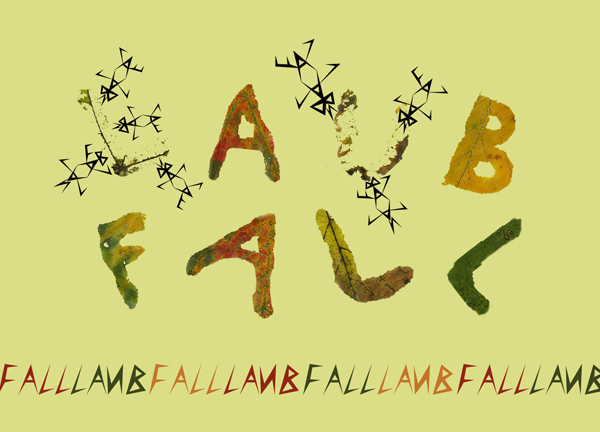
Cunei font gesucht
Hallo, auf meinem alten Computer (der sich für immer verabschiedet hat) war anscheinend eine Schrift vorinstalliert, die jetzt nicht mehr vorhanden ist: Cunei font. Auch auf meiner Schriften-CD und hier in der Forensammlung ist sie nicht zu finden. Hat jemand diese Schrift noch? Anbei ein Bild, in das ich die Schriftzeichen eingebaut hatte. Vielen Dank für eure Hilfe!
Super, danke für die schnelle Antwort! Ja, die Ähnlichkeit mit Insektenbeinen ist unübersehbar und das geht mit keiner anderen Schrift so gut. ;)
oder so etwas
die mir neben Aarcover in x verschiedenen Namen üver den Weg gelaufen ist, und von der ich nicht sagen kann, was davon Plagiat, Clone, Original oder sonst was ist
Ja, die sind auch nicht schlecht! Mal schauen, welche Tierchen oder Gegenstände sich daraus erstellen lassen. Danke!